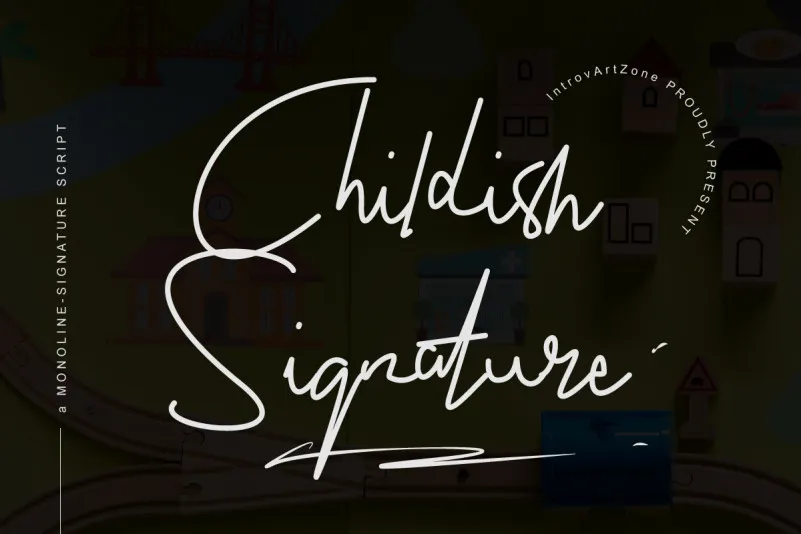
A IntrovArtZone apresenta com orgulho a família de fontes “Childish Signature Font”, uma fonte monoline escrita à mão no estilo de uma assinatura. Essencialmente simples, mas ainda elegante, essa fonte é perfeita para um uso variado que pode incluir capas de livros, citações, convites de casamento, design gráfico, impressão e design web, marca ou qualquer outro propósito. Com um toque infantil na sua simplicidade, a Childish Font oferece uma combinação única entre elegância e simplicidade, fazendo-a ideal para designers que buscam um estilo único em suas criações. A fonte é perfeita tanto para designer gráfico profissional quanto para aqueles iniciantes que desejam dar um toque especial à sua identidade visual.